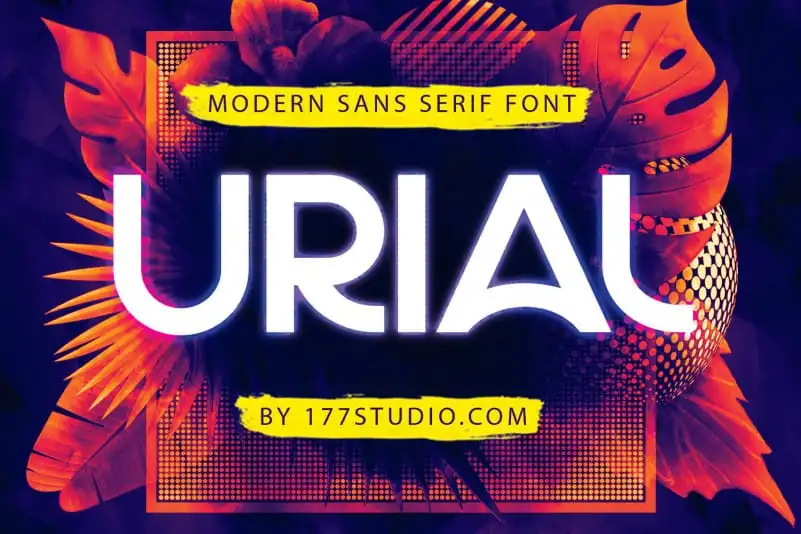
URIAL Sans Font Family – Download Grátis
URIAL Sans é uma famosa família de 9 tipos modernos que oferece a você designers inúmeros possíveis usos. Essa extensa coleção é perfeita para qualquer tipo de projeto, seja ele do campo da moda e invitations de festas, até editoriais, cinema ou blogs. Seu estilo clean e minimalista torna-o uma escolha ótima tanto para publicações tradicionais quanto para mídias digitais, como blog header, postagens em redes sociais, banners de adesivos e etiquetas no supermercado. Com URAIL Sans, você terá a liberdade de transformar qualquer projeto graças à sua versatilidade. Ideal tanto para branding, quando se trata da criação de marcas visuais distintas e memoráveis, quanto para fontes de blog e t-shirts personalizadas – todas as suas propostas criativas ficam perfeitamente em sintonia com esta família de tipos. Combinar este design moderno com seu estilo minimalista, URAIL Sans é uma solução ideal para se tornar o arquiteto visual do seu próximo projeto. Seja ele um site ou blog, um livro ou uma capa de revista, o lançamento de um novo produto ou a criação de um logo, certamente terá o aspecto perfeito e elegante com esta família de tipos que oferece um design limpo e sofisticado.